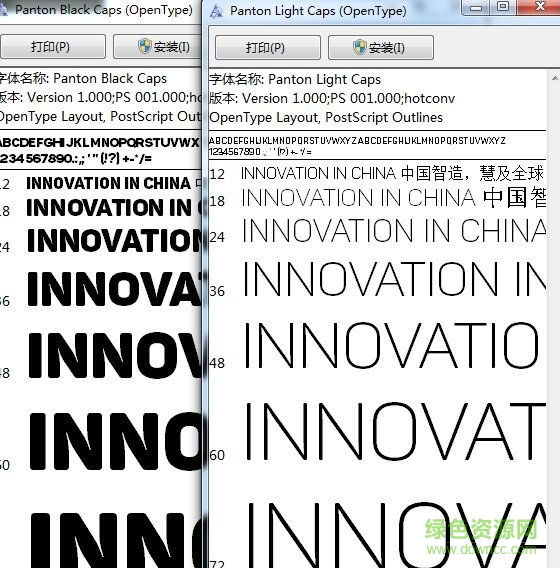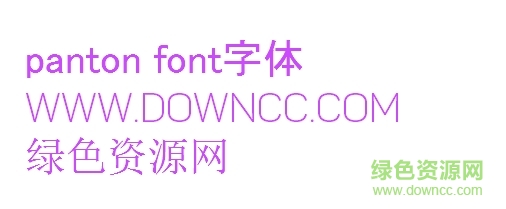
panton font
panton是一款免費(fèi)的英文字體,本系列共有四款字體,給你簡(jiǎn)單大方的造型設(shè)計(jì)體驗(yàn),一起來(lái)綠色資源網(wǎng)下載收藏吧!
panton font介紹
panton字體包括:Panton-BlackCaps、Panton-BlackitalicCaps、Panton-LightitalicCaps,有著粗細(xì)、傾斜的區(qū)別,是一款高質(zhì)量的英文字體!
綠色資源網(wǎng)小編點(diǎn)評(píng)
PANTON字體整體效果非常的出色,字形端正鮮明亮麗,線條較粗較胖,且字庫(kù)完整,可以廣泛應(yīng)用于美術(shù)設(shè)計(jì)、廣告設(shè)計(jì)、宣傳海報(bào)、ppt、影視制作等領(lǐng)域!